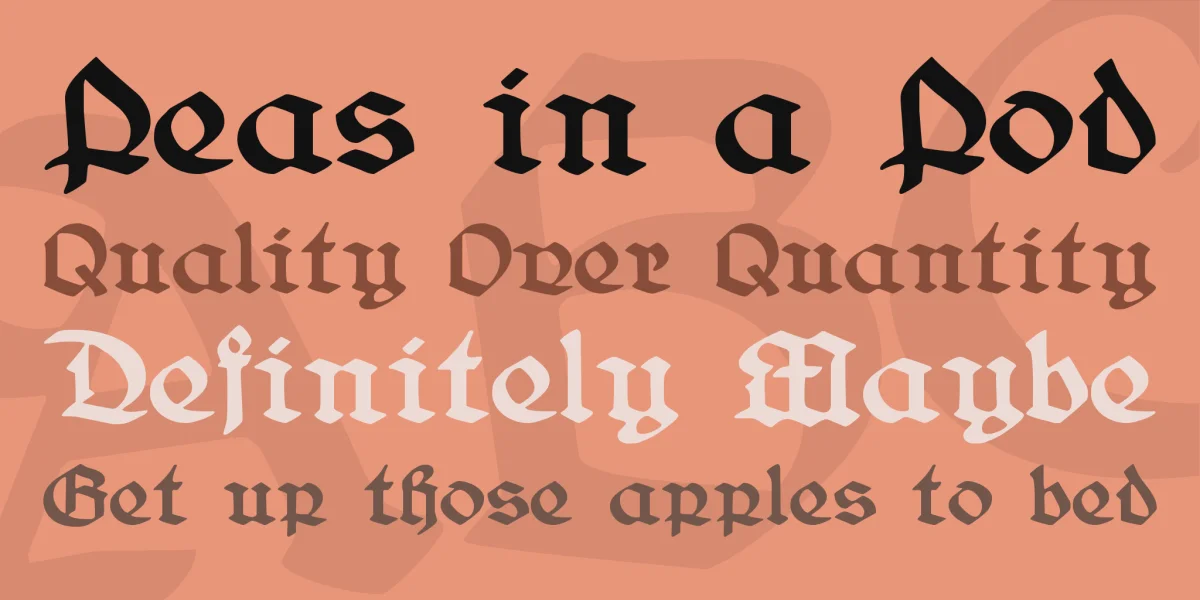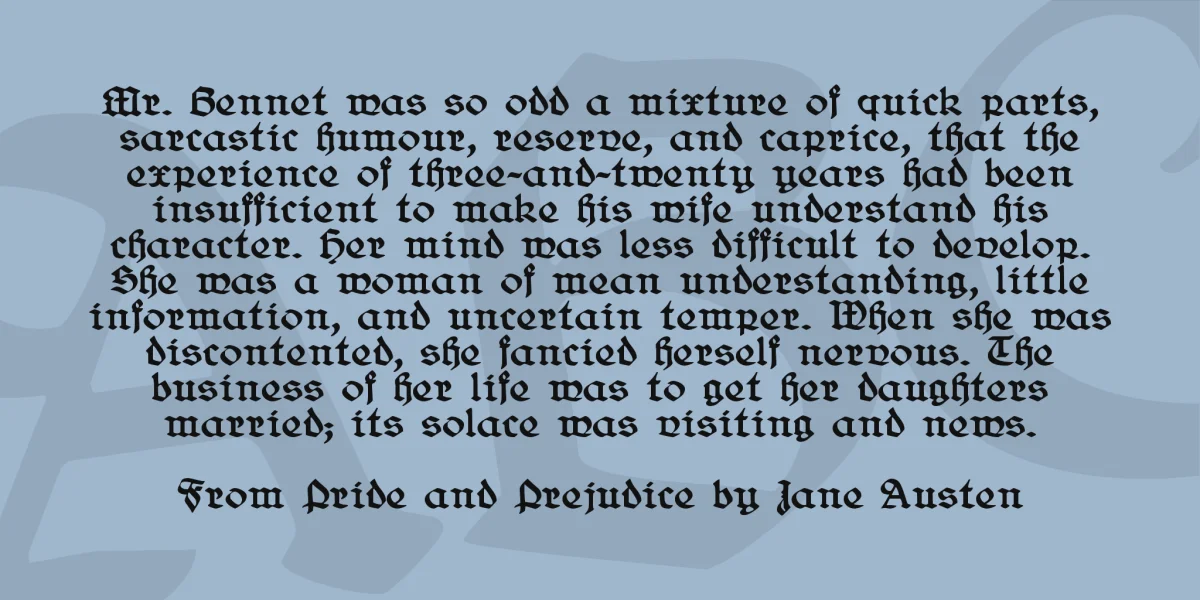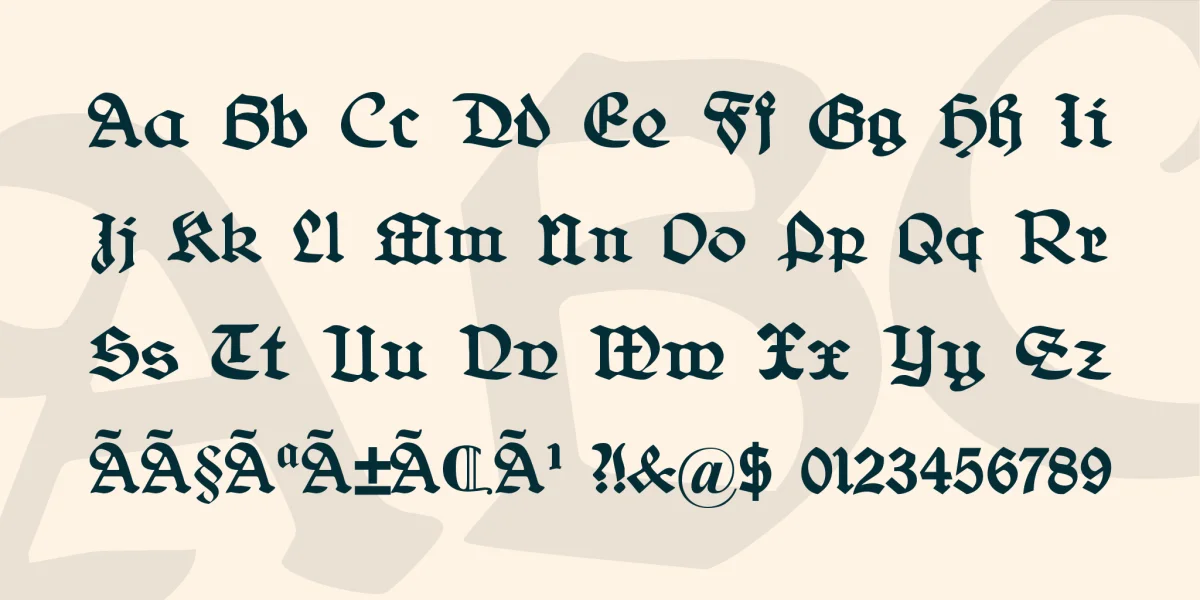
Digitalisiert von Dieter Steffmann, Kreuztal. Nach Entwuerfen von Georg Belwe, Professor an der Koeniglichen Akademie fuer Graphische Kuenste und Buchgewerbe zu Leipzig fuer die Schriftgiesserei J. G. Schelter & Gieseke, Leipzig (ca. 1913)